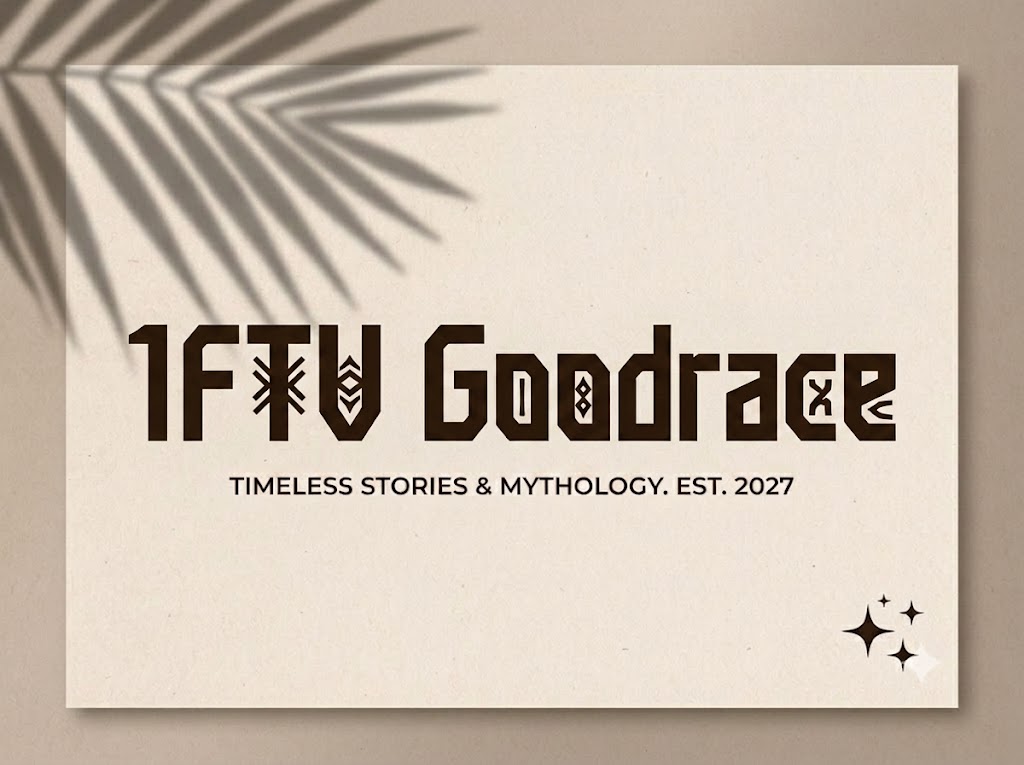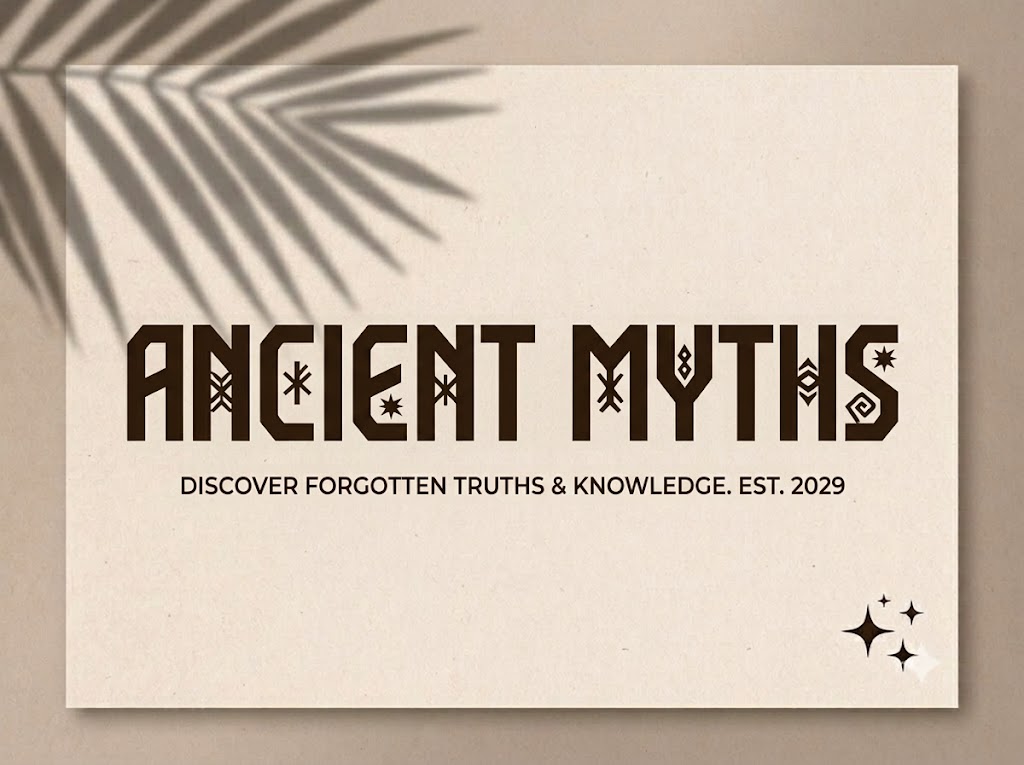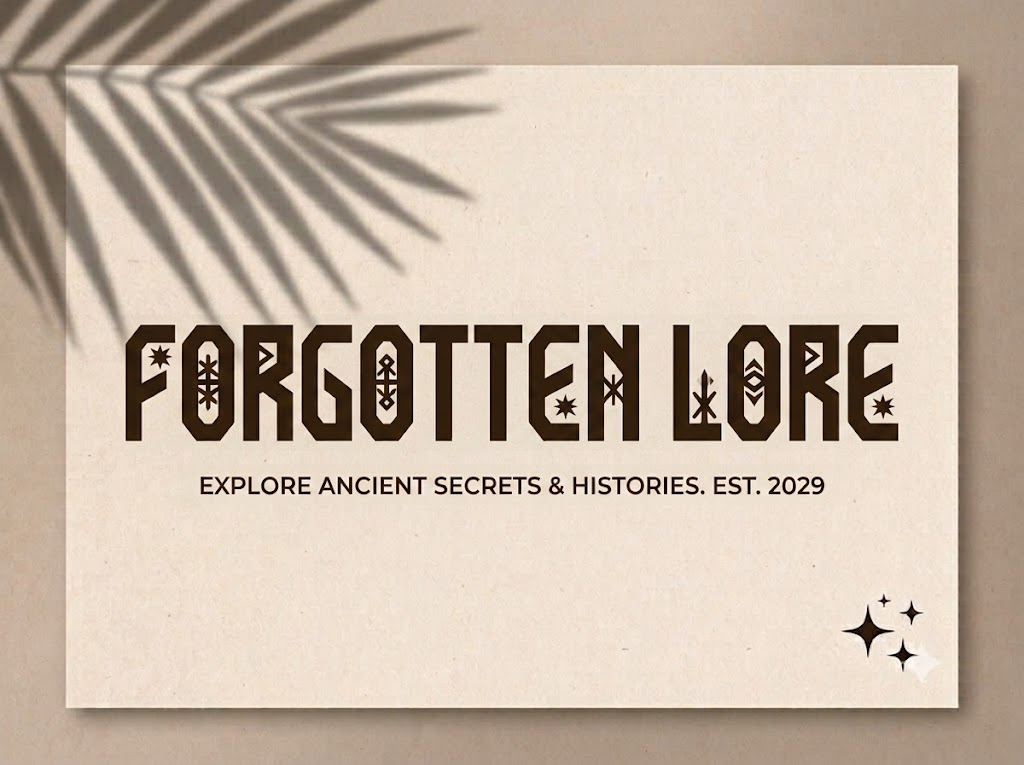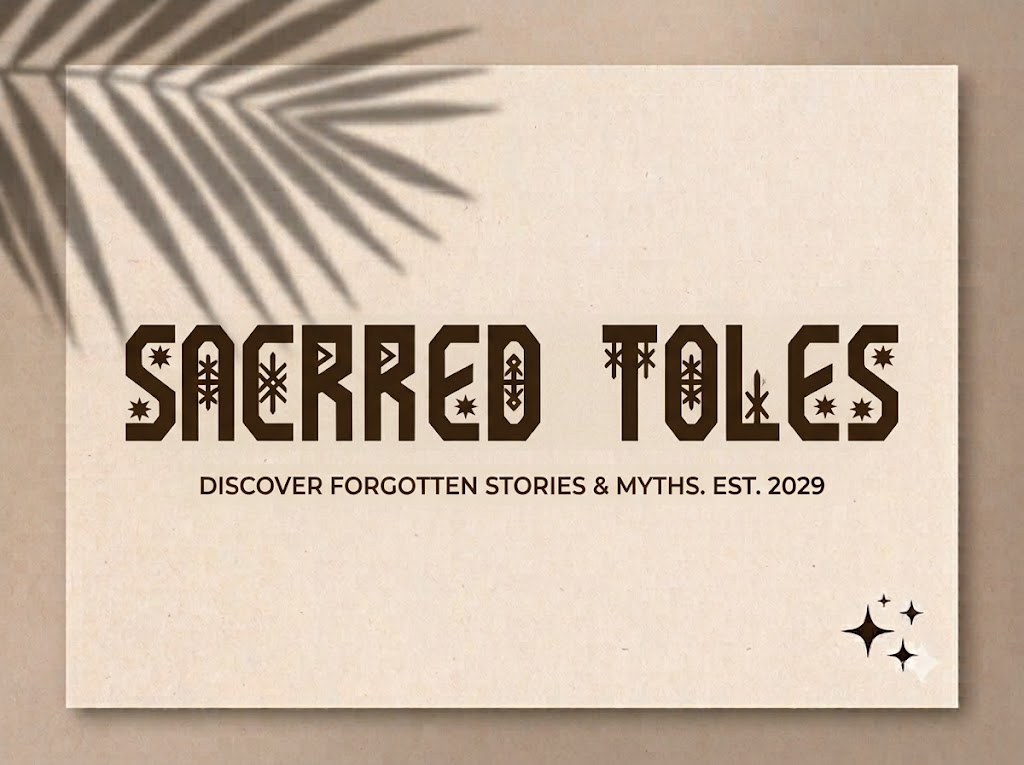
1FTV Goodrace
Trong xu hướng sáng tạo nội dung số hiện nay, các phông chữ hiển thị (display font) với đường nét dày dặn, góc cạnh luôn là lựa chọn hàng đầu để tạo ra sự đột phá về mặt thị giác.
Một dòng tiêu đề ấn tượng không chỉ giúp truyền tải thông điệp nhanh chóng mà còn định hình phong cách mạnh mẽ, cá tính cho toàn bộ tác phẩm đồ họa.
Nếu bạn đang tìm kiếm một bộ chữ không chân mang tinh thần thể thao, tốc độ và hiện đại, thì font 1FTV Goodrace chính là giải pháp không thể bỏ qua.
Giới thiệu về font 1FTV Goodrace
Font 1FTV Goodrace là một phông chữ hiển thị không chân (sans-serif) được thiết kế nhằm mang lại cảm giác năng động, vững chãi và vô cùng bứt phá.
Được chia sẻ rộng rãi bởi đội ngũ 1FTV, đây là bộ font độc đáo dành riêng cho cộng đồng designer và editor chuyên nghiệp tại Việt Nam.
Đặc điểm nổi bật của phong cách thiết kế Goodrace
Sức hút lớn nhất của font 1FTV Goodrace đến từ cấu trúc chữ khối dày dặn kết hợp cùng các đường cắt góc (vát góc) vô cùng táo bạo và dứt khoát.
Cảm hứng tạo hình của font chữ gợi liên tưởng mạnh mẽ đến những đường đua tốc độ, ngành công nghiệp ô tô hay thế giới trò chơi điện tử sôi động.
Điểm cộng rất lớn của bộ font này là việc hỗ trợ trọn vẹn cả hệ thống chữ hoa lẫn chữ thường đồng bộ, mang lại sự linh hoạt tối đa khi sắp xếp bố cục văn bản cho các nhà thiết kế.
Các khoảng hở bên trong ký tự (counter) được tính toán khoa học giúp các khối chữ dù siêu đậm nhưng vẫn giữ được sự thông thoáng, rõ ràng và không bị dính đặc khi đứng cạnh nhau.
Hệ thống khoảng cách chữ (kerning) và độ giãn dòng đã được căn chỉnh chuẩn xác, giúp văn bản luôn liền mạch và giữ được sự thoáng đãng thẩm mỹ tốt nhất.
Bên cạnh hệ thống chữ cái hoa và thường đồng bộ, phông chữ còn tích hợp đầy đủ dãy số từ 0-9 cùng hệ thống các ký tự đặc biệt, dấu câu thông dụng (1234567890.:,;'"(!?)+-*/=).
Đặc biệt, bản Việt hóa chuẩn chỉnh này giúp bạn hoàn toàn yên tâm sáng tạo các nội dung quảng cáo hay làm sub video tiếng Việt mà không lo gặp phải tình trạng lỗi hiển thị hay nhảy font.
Hình ảnh demo thực tế của font 1FTV Goodrace
Để giúp bạn dễ dàng hình dung khả năng co giãn và hiển thị linh hoạt của phông chữ này trên các kích thước khác nhau, hãy cùng xem qua bảng mô phỏng thực tế từ file hệ thống image_a0d199.png:
Kích thước nhỏ (12pt – 24pt): Các nét chữ đậm góc cạnh và bộ chữ thường vẫn hiển thị rất rõ ràng, ngay ngắn, dễ đọc trên màn hình điện thoại di động.
Kích thước lớn (36pt – 72pt): Đây là đất diễn lý tưởng để font chữ phô diễn toàn bộ sức mạnh hình khối thể thao, tạo hiệu ứng thị giác mạnh mẽ cho các tiêu đề chính.
Ứng dụng của font Goodrace trong thiết kế đồ họa và làm video
Sở hữu nét cá tính mạnh mẽ và cấu trúc hoa – thường linh hoạt, font 1FTV Goodrace mở ra không gian ứng dụng rộng lớn cho các dự án truyền thông và marketing:
Thiết kế ảnh thu nhỏ YouTube (Thumbnail): Đây là vũ khí hạng nặng để tăng tỷ lệ nhấp chuột cho các video thuộc chủ đề gaming, review xe, đồ công nghệ hoặc các nội dung hành động, thể thao.
Làm tiêu đề video ngắn (TikTok, Shorts, Reels): Dáng chữ cứng cáp, bắt mắt giúp các câu từ khóa chính hay tiêu đề mở đầu video nổi bật ngay lập tức để giữ chân người xem lướt chậm lại.
Banner và poster quảng cáo giải đấu: Hoàn hảo cho các poster giải đấu thể thao điện tử (esports), banner câu lạc bộ gym, fitness, phụ tùng cơ khí hoặc các sự kiện năng động của giới trẻ.
Nhận diện thương hiệu phong cách đường phố: Phù hợp làm logo dạng chữ khối, artwork in ấn cho các thương hiệu thời trang streetwear hoặc nhãn mác sản phẩm cần sự nam tính, phá cách.